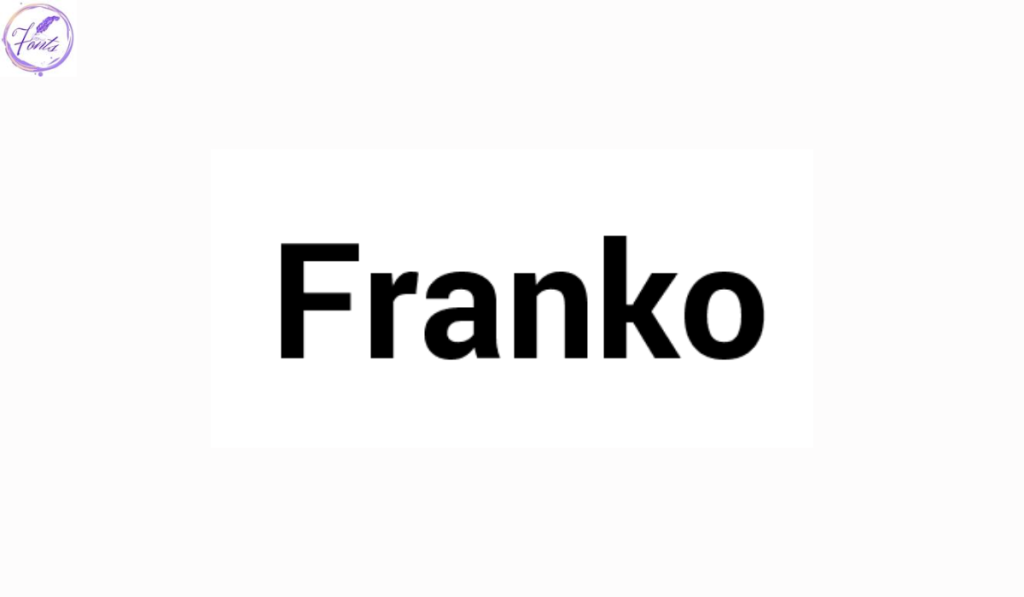
Font Franko việt hóa
Tác giả: Rix Fonts
Ngày phát hành: 2021
Ngôn ngữ: Tiếng Việt, Tiếng Anh, và nhiều ngôn ngữ khác
Việt hóa: MTD Fonts
Bộ Font: Franko
Phân loại: Sans-serif, Geometric
Kiểu chữ: Không chân, Geometric
Độ dày: Regular, Condensed
Font Franko là một font chữ hiện đại và thanh lịch, được thiết kế bởi Rix Fonts vào năm 2021. Với các đường nét rõ ràng và tinh tế, font này rất phù hợp cho các dự án thiết kế đòi hỏi sự tinh giản và sang trọng. Font Franko nổi bật với sự kết hợp hài hòa giữa các nét thẳng và cong, tạo nên một vẻ đẹp độc đáo và dễ nhận diện. Với sự hỗ trợ đầy đủ các ký tự tiếng Việt, font Franko là lựa chọn tuyệt vời cho các nhà thiết kế muốn tạo ra những tác phẩm đậm chất riêng.
Đánh giá font franko
Font Franko được đánh giá cao bởi tính ứng dụng đa dạng và tính thẩm mỹ cao. Người dùng yêu thích font này vì nó dễ dàng kết hợp với nhiều phong cách thiết kế khác nhau, từ hiện đại đến cổ điển. Ngoài ra, font Franko còn được tối ưu hóa cho các thiết bị số, đảm bảo hiển thị rõ ràng và sắc nét trên mọi màn hình. Những đặc điểm này giúp font Franko trở thành một công cụ đắc lực trong kho vũ khí của bất kỳ nhà thiết kế nào.